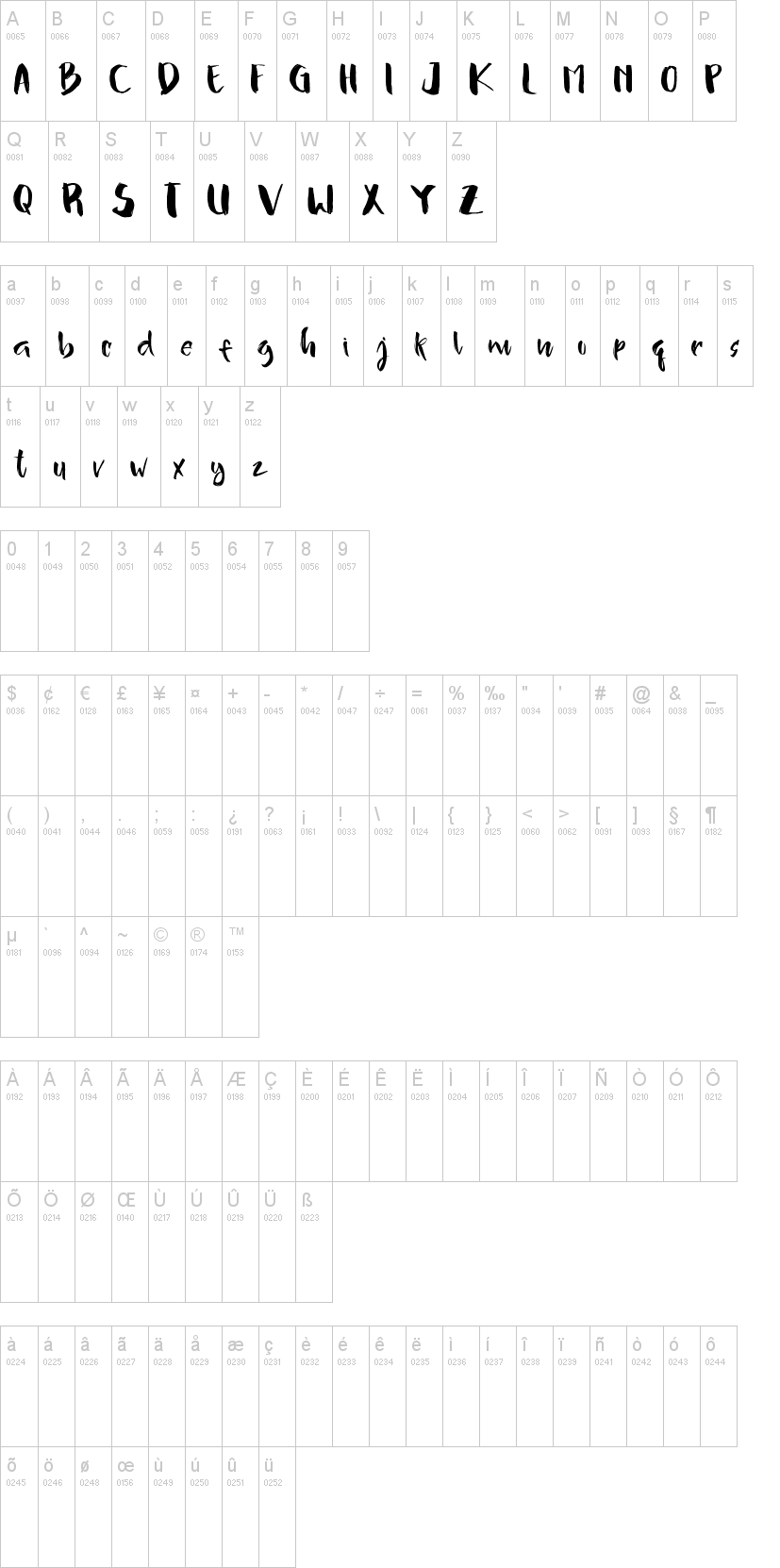
Valentine Season
? Valentine Season 字体是一款特别适合用于情人节的手写体字体,它具有浪漫、可爱、时尚的特点,极具浪漫气息。它的字形丰富,包括大写字母、小写字母和标点符号,以及精致的细节,可以帮助你创造出一种温暖的氛围。它还可以用于制作精美的贺卡、海报、电子邮件、网页和其他设计作品,帮助你表达你的爱意。
Valentine Season是一款非常不错的手写艺术字体,具有很好的视觉感,适合于文化类的宣传设计、商业类品牌的广告和产品包装设计以及个性化文字排版等较多场景。
Valentine Season字符映射图